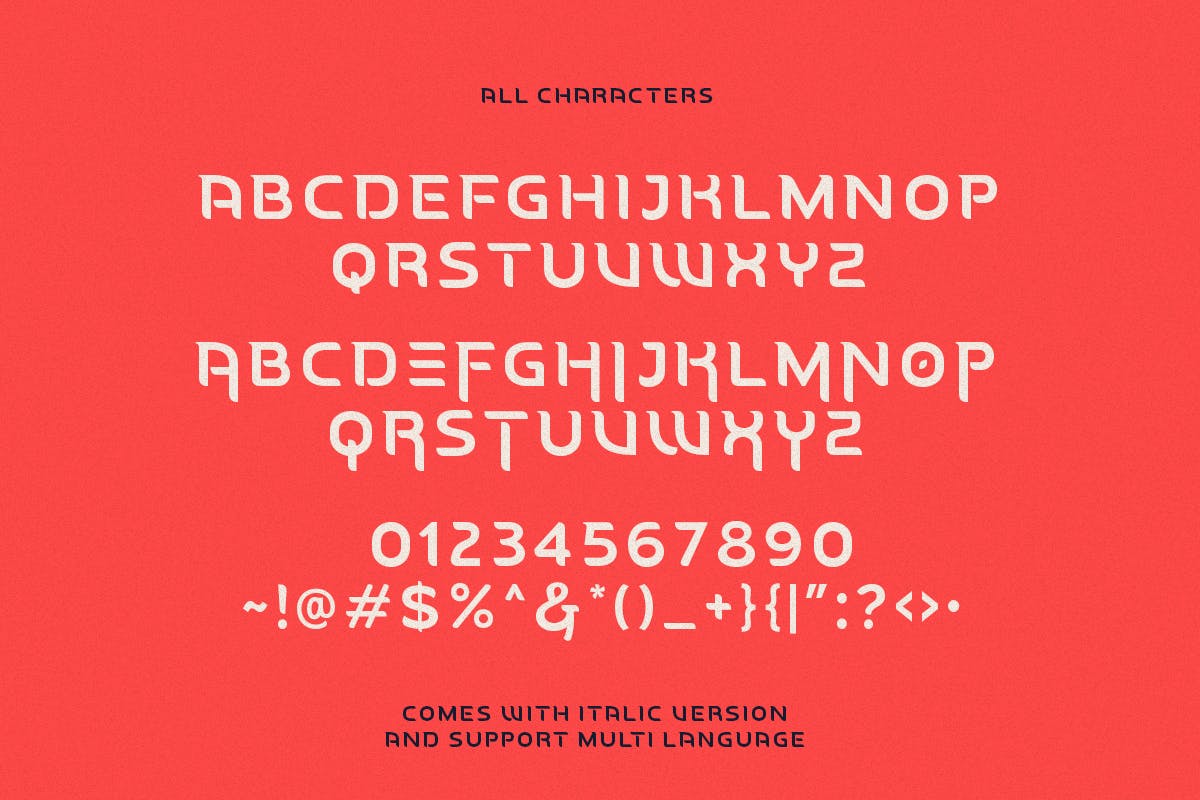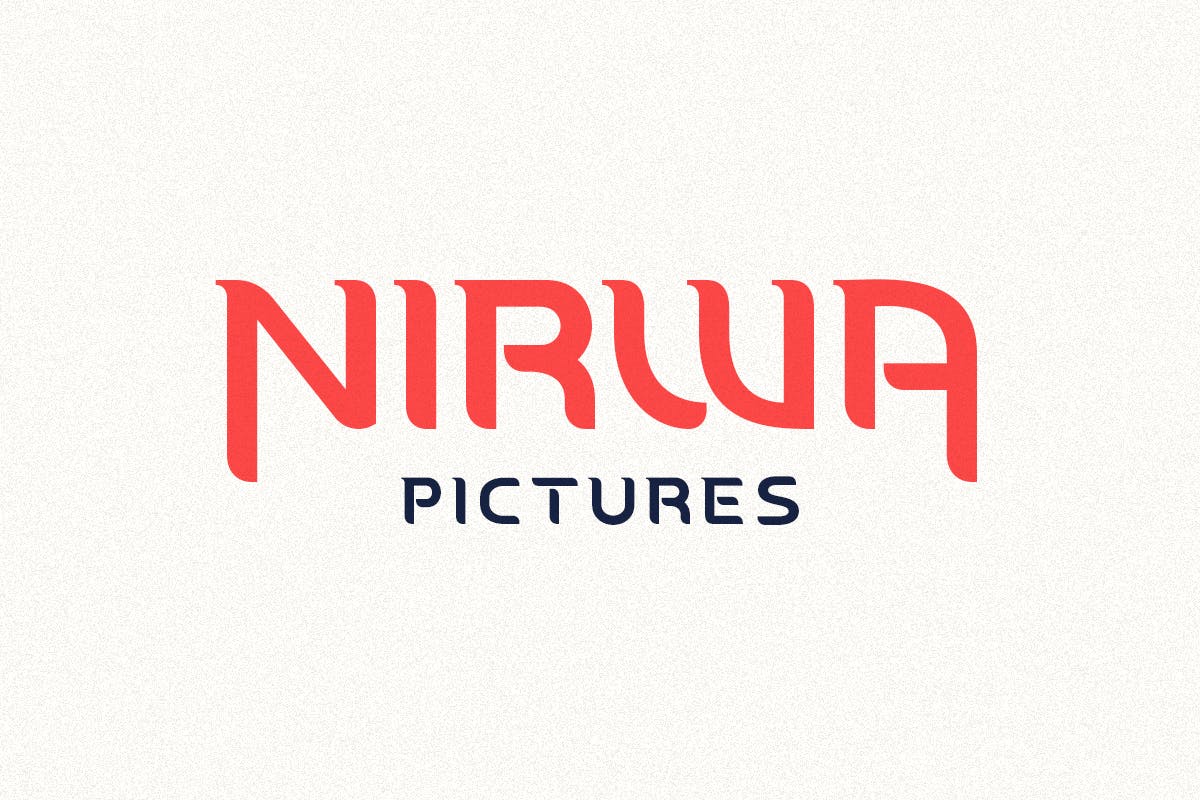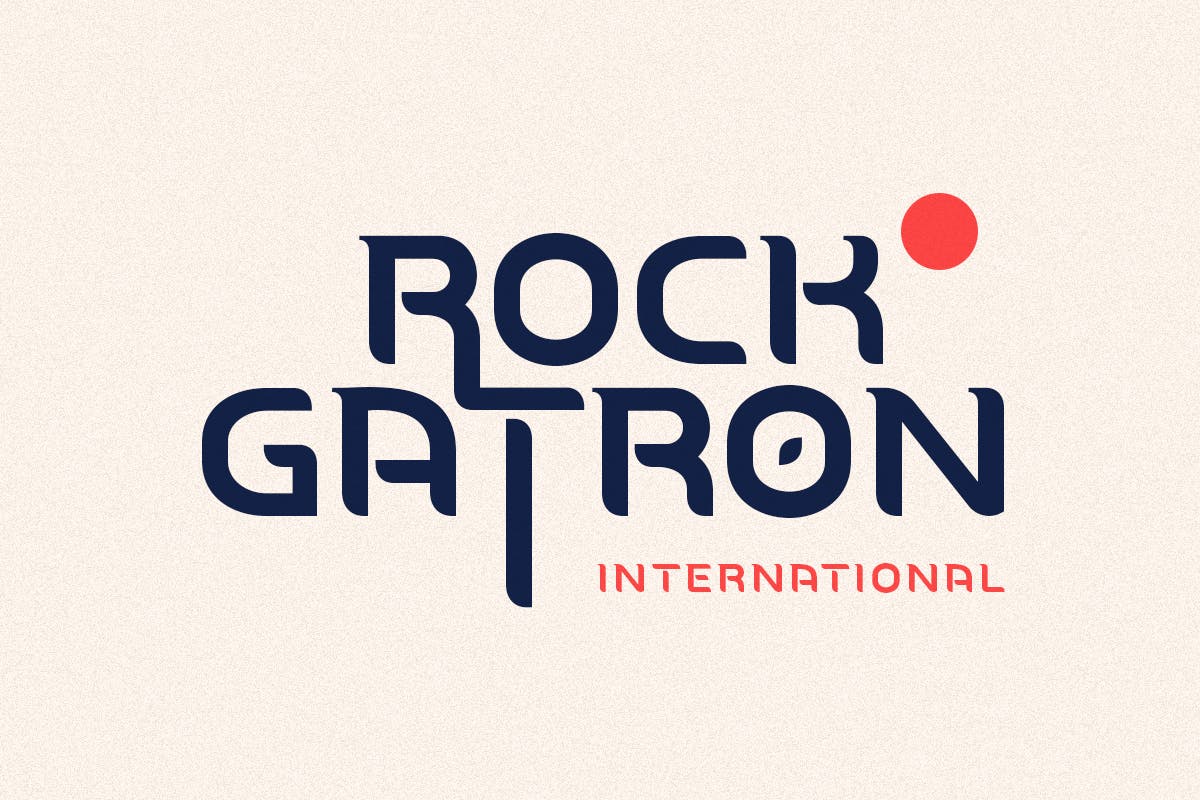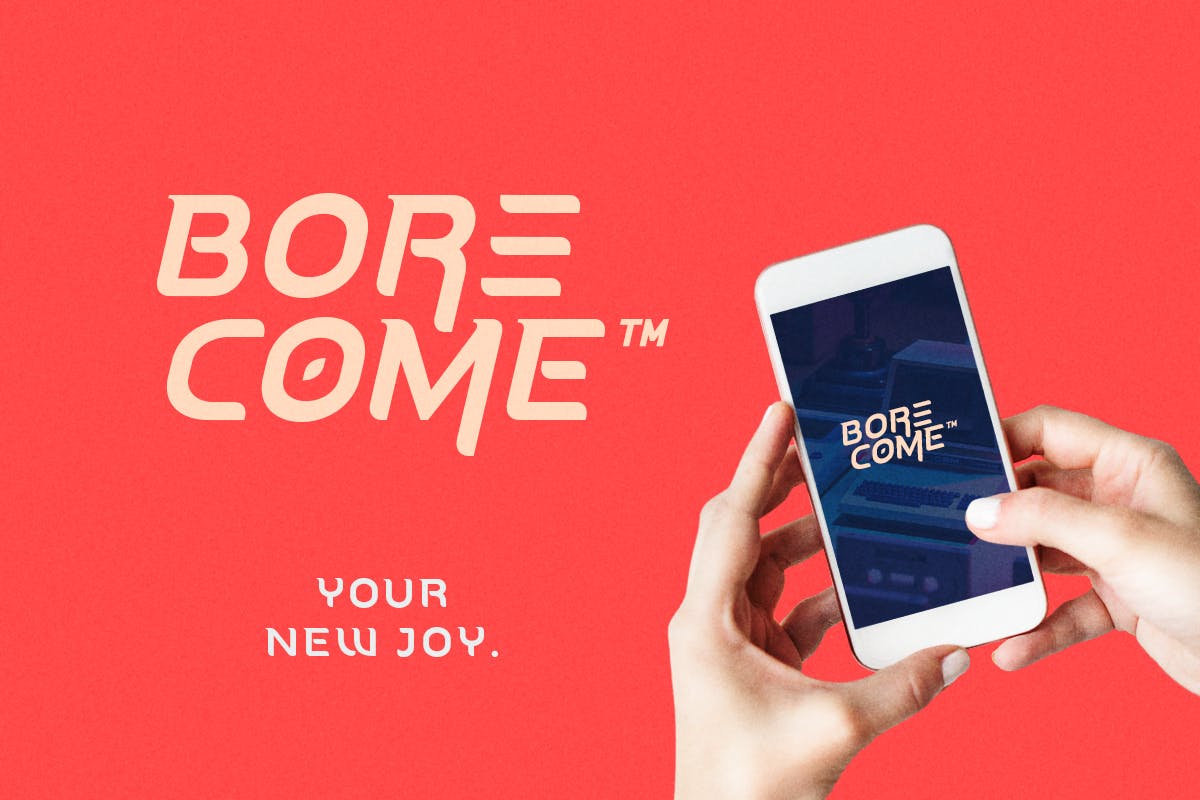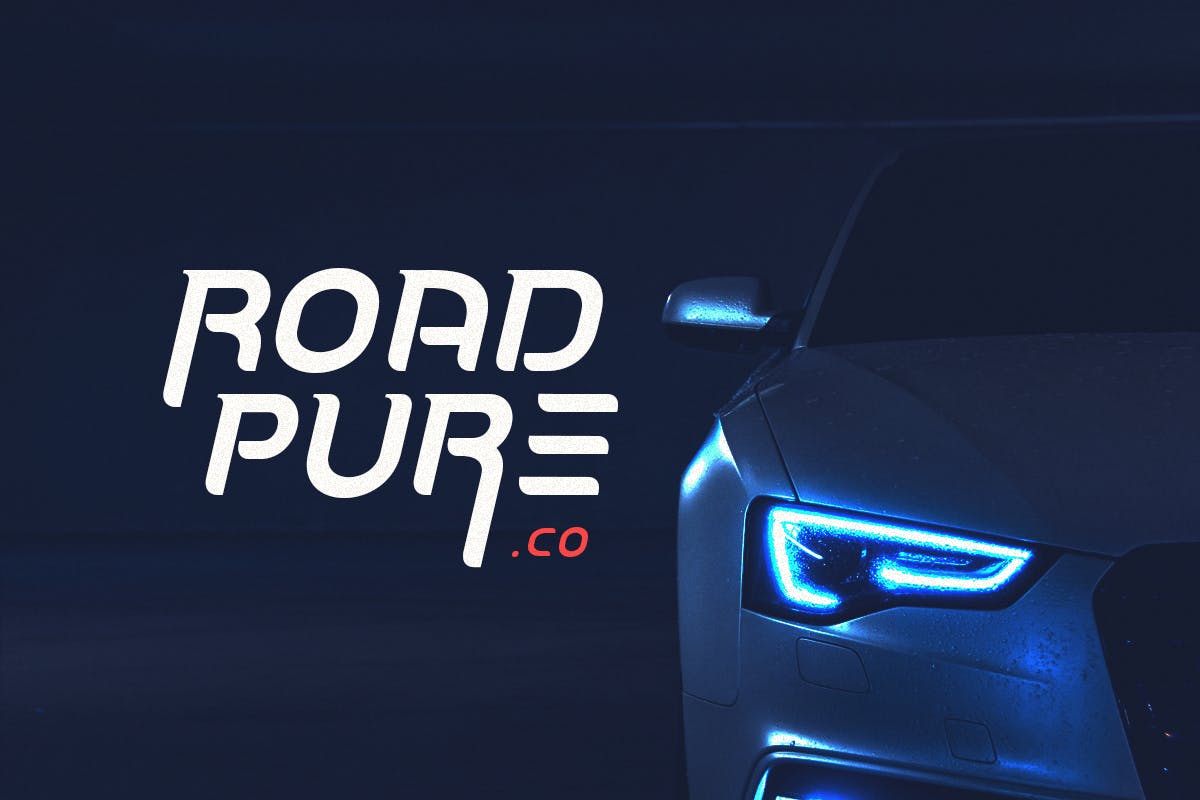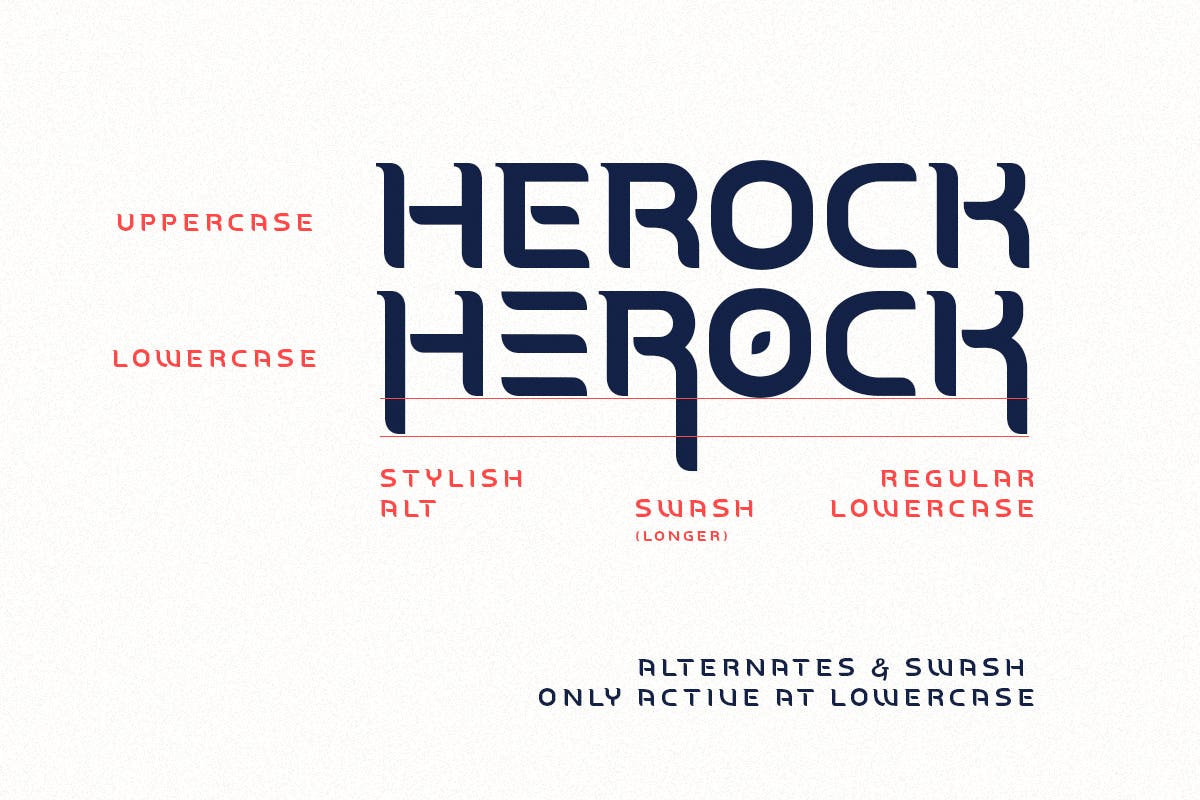
هاردیپ یک فونت لوگو با طراحی منحصر به فرد است که به لوگو و طراحی شما ظاهری ساده و شیک میبخشد. با ویژگیهای خاص حروف کوچک، این فونت میتواند لوگوی شما را جذابتر کند. شما میتوانید از این فونت برای هر منظوری استفاده کنید، بهویژه برای ساخت لوگوتایپ. امکان ترکیب حروف بزرگ و کوچک برای برجستهتر کردن لوگو وجود دارد. هاردیپ همچنین دارای نسخه ایتالیک است که حس متفاوتی را منتقل میکند. این فونت شامل اعداد، نمادها و پشتیبانی از زبانهای چندگانه نیز میباشد!